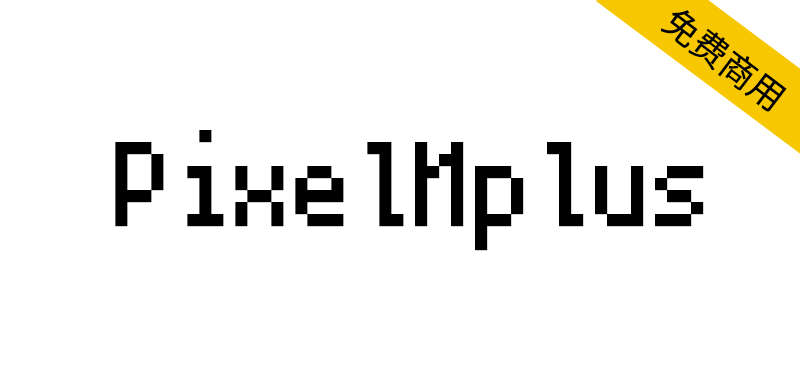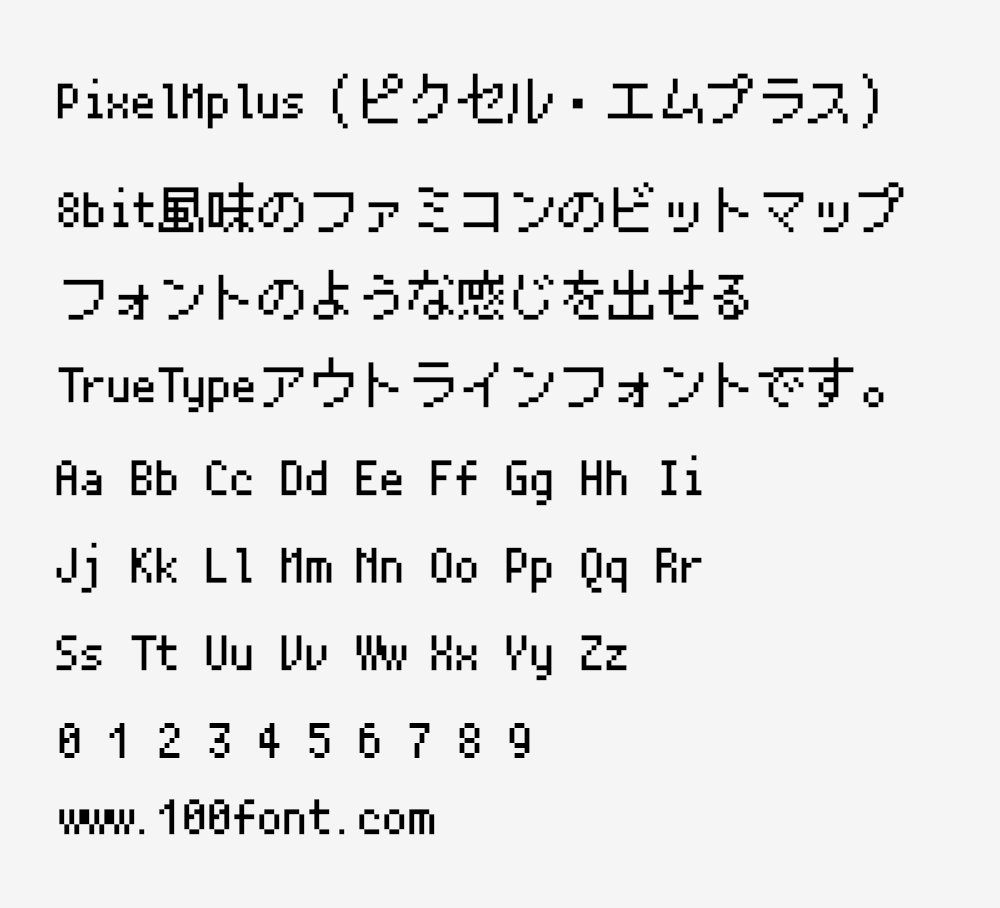
PixelMplus(ピクセル・エムプラス)是一款TrueType轮廓字体,让人感觉像是8bit风格的点阵像素字体。但只有轮廓,没有嵌入位图,包括粗体。收录了JIS第1、第2水准的所有字符,还收录了ISO-8859-1(Latin-1)的字符,除此之外还追加了一些其他符号。它实际是一个TrueType等宽字体,也可以在文本编辑器中使用。有PixelMplus12和PixelMplus10两种字体,区别在于原始位图字体是12像素还是10像素,两者的大小相同。
8bit風味のファミコンのビットマップフォントのような感じを出せる TrueTypeアウトラインフォントです。
ビットマップフォントのように見えるが、アウトラインのみのTrueTypeフォント。 埋め込みビットマップは なし。ボールド体(太字)あり。
JIS第1・第2水準のすべての漢字を収録。ISO-8859-1(Latin-1)の文字も収録。 そのほかにもいくつかの記号を追加。
実体は単なるTrueType等幅フォント。テキストエディターで使用することもできる。
PixelMplus12 と PixelMplus10 の2種類のフォントがあります。 元にしたビットマップフォントが 12ピクセルであるか、10ピクセルであるか、の点が違います。